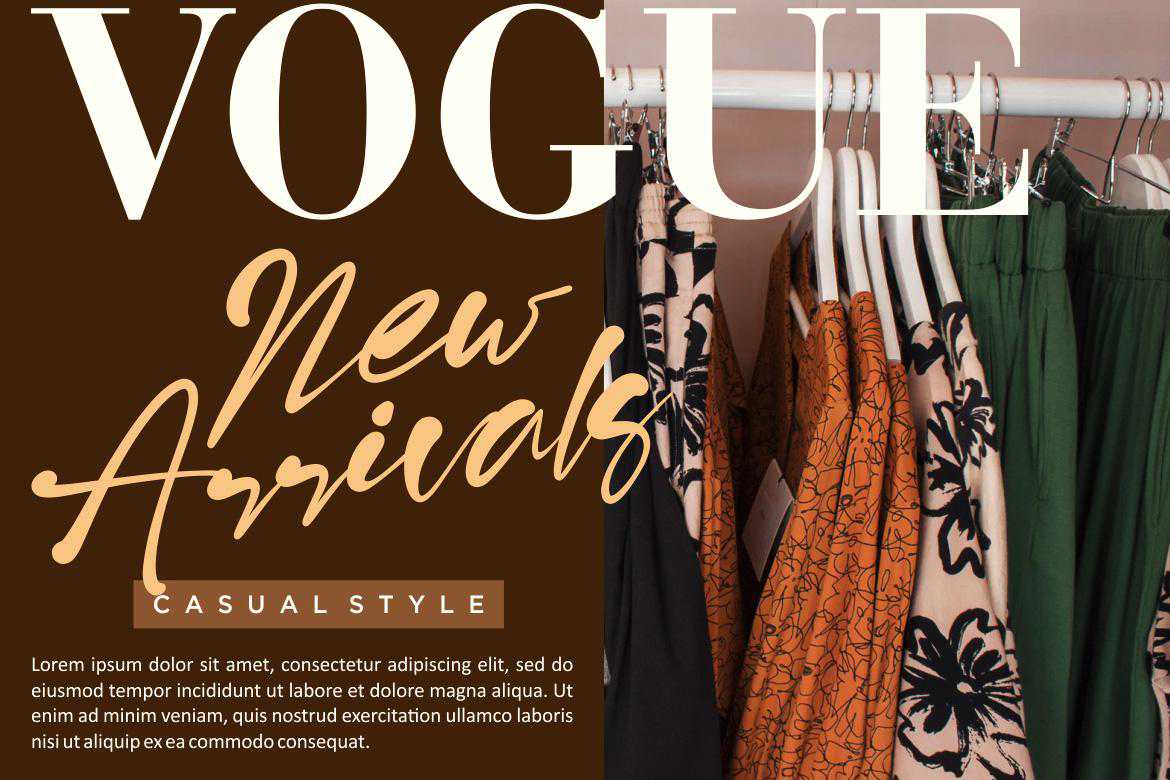
RISOLLACALIST是一种美观、粗体、现代的手写字体。此字体中还提供了几种可选的字体。此字体非常适合创建徽标、水印、品牌、婚礼宣传、报价或任何内容。让我们用此字体创建一些漂亮的项目。RISOLLACALIST是一种美观的字体,BoldandModern和WriteTenscript字体。此字体中还提供了几种可选的字体。此字体非常适合创建徽标、水印、品牌、婚礼宣传、报价或任何内容。让我们用它来创建一些美丽的项目。